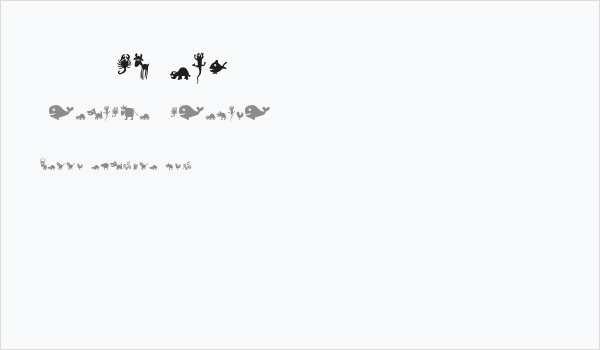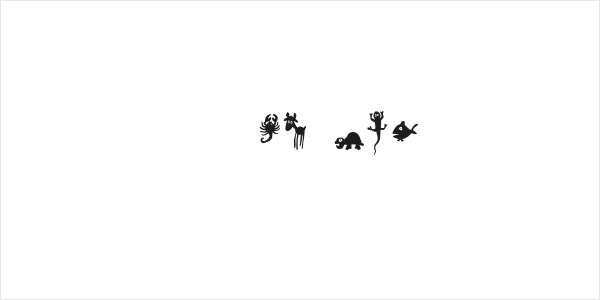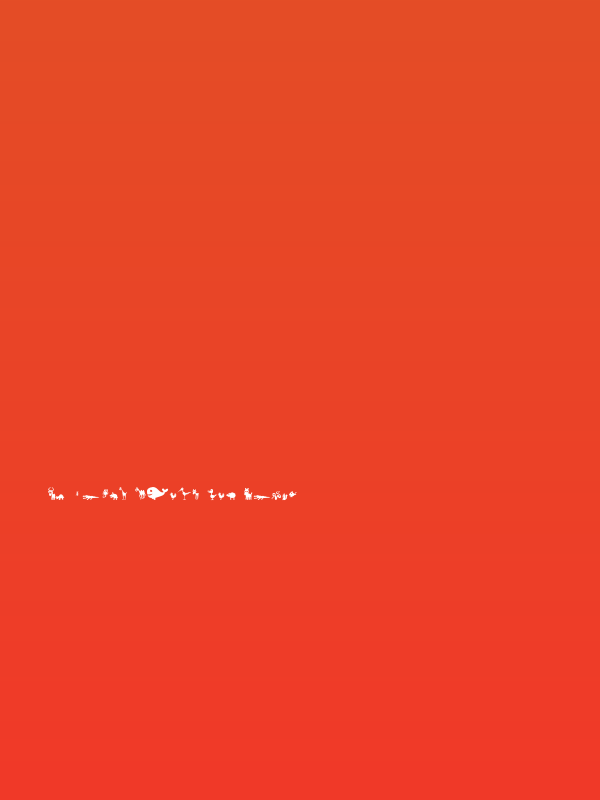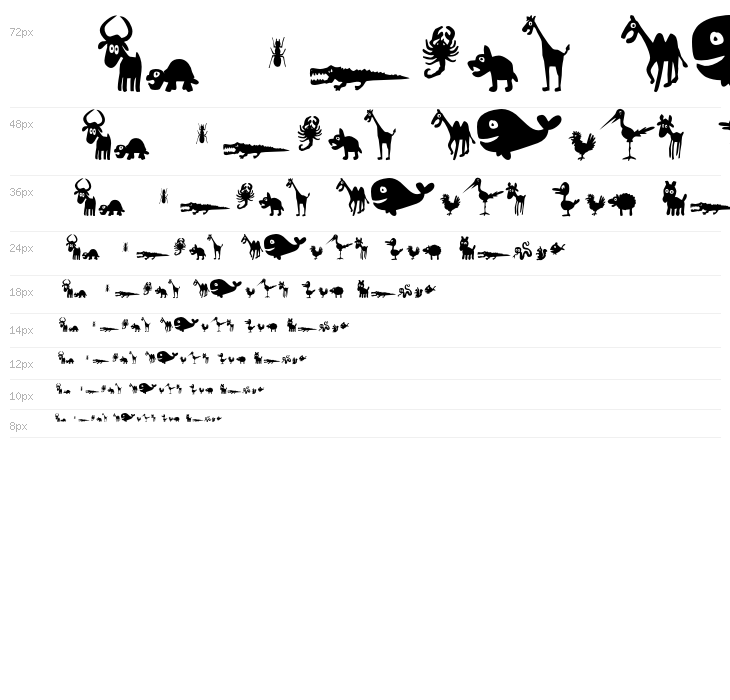
FE-WinPets2 Font
✎ Dingbats
| समग्र शैली | Playful, Whimsical, Decorative |
| उपयोग का मामला | Icons, Decorative elements, Children’s content, Themed event materials |
| सुझाए गए प्रोजेक्ट | Children’s books, educational materials, posters, greeting cards, playful branding, stickers. |